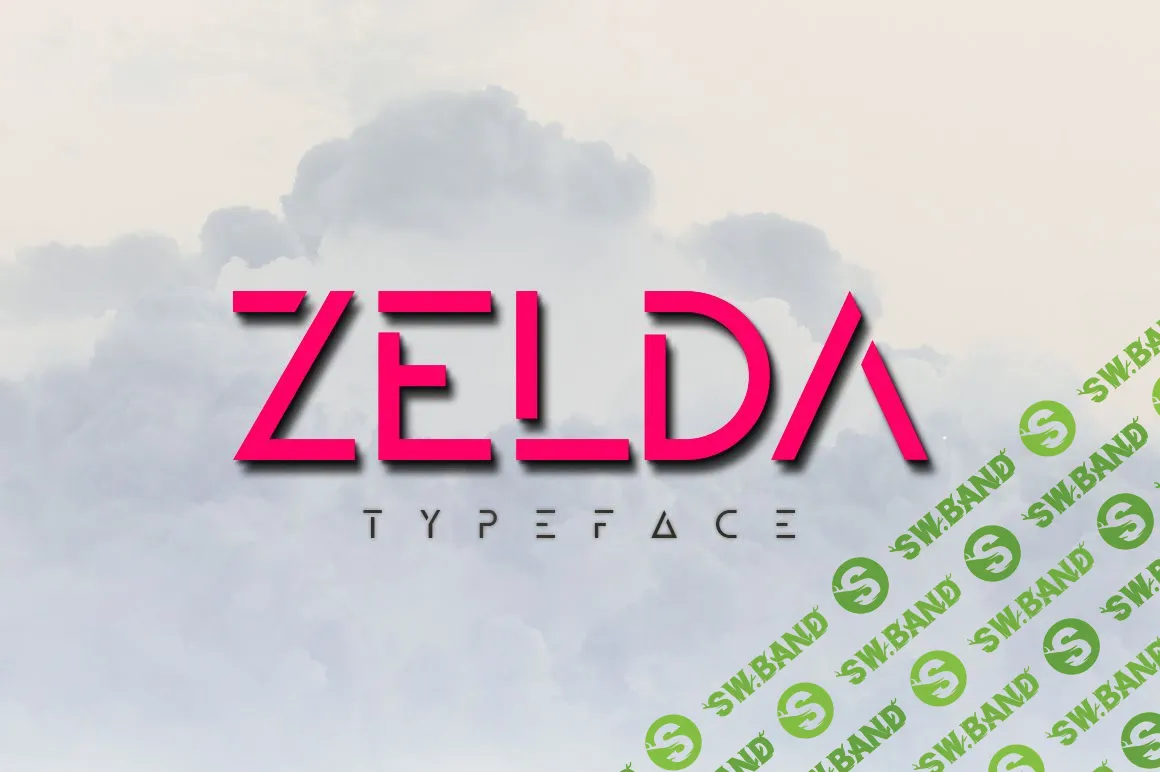
Название: ZELDA Typeface (Fill)
Привет ребята! Я очень рад поделиться своим новым шрифтом ZELDA!
ZELDA - это миниатюрный шрифт для дисплея, вдохновленный классическим семейством шрифтов без засечек. Этот шрифт идеально подходит для логотипов / постеров и заголовков.